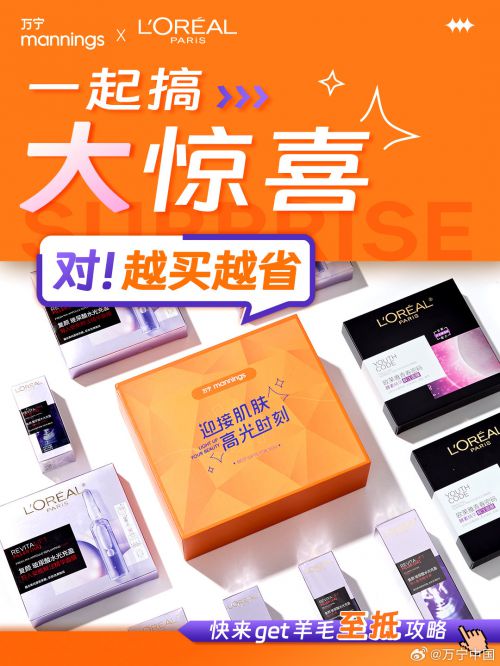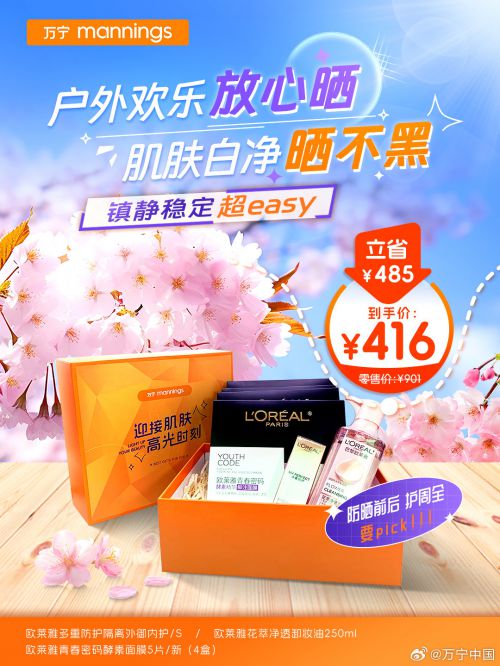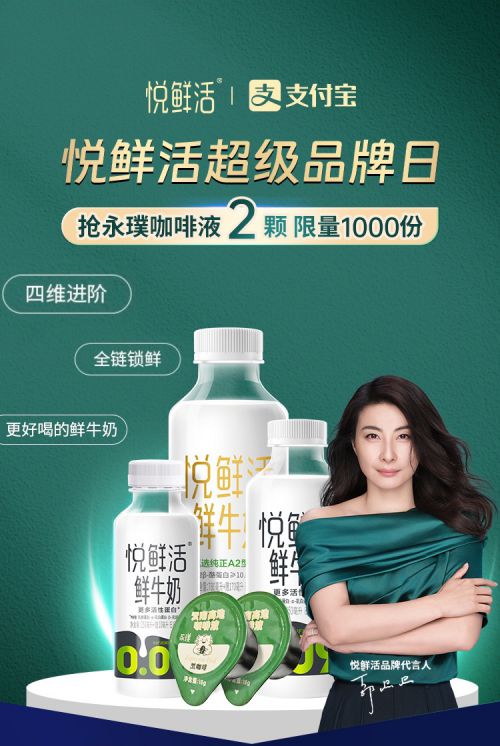
钉钉进步体
字库品牌: Alibaba
钉钉进步体是由Alibaba联合汉仪字库打造的原创黑体字体,以现代简约风格为核心,专为标题与美术字场景设计。作为一款兼具科技感与书写美的专业字库,字体结构方正稳健,重心居中且中宫宽博,整体字形舒展大气;笔型融合直角与斜切元素,方头笔画搭配均匀粗线条,既保留黑体的利落质感,又通过笔画断开的细节增添灵动感,让文字兼具力量与韵律。 钉钉进步体涵盖中、英文7526个常规字符,字符集丰富,可满足多样设计需求。作为永久免费商用字体,它打破版权壁垒,助力个人与中小组织轻松获取高质量设计资源,让现代设计中的文字表达更自由——无论是科技主题宣传、品牌标题设计,还是创意美术排版,钉钉进步体都能以独特的风格传递进步力量,成为兼具实用性与艺术性的优选黑体字库。